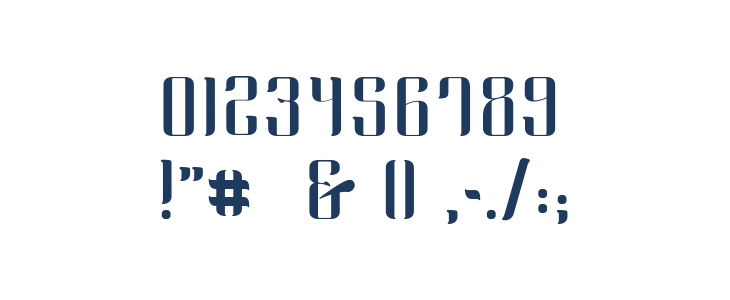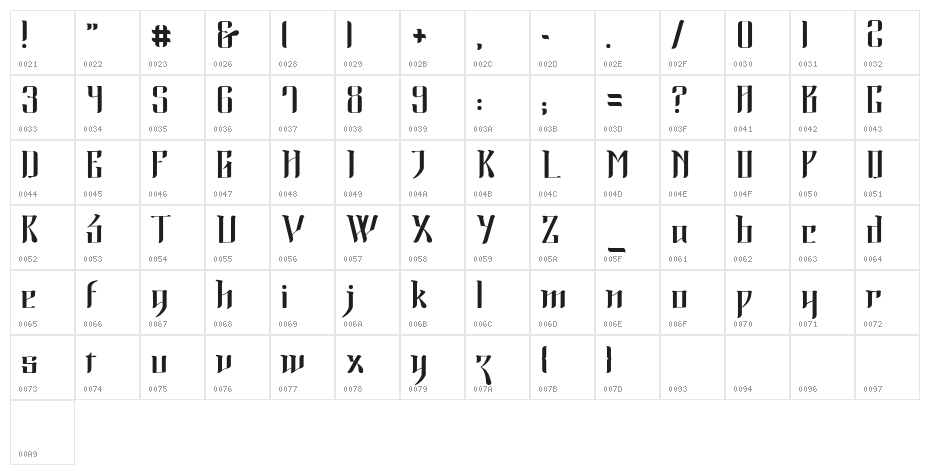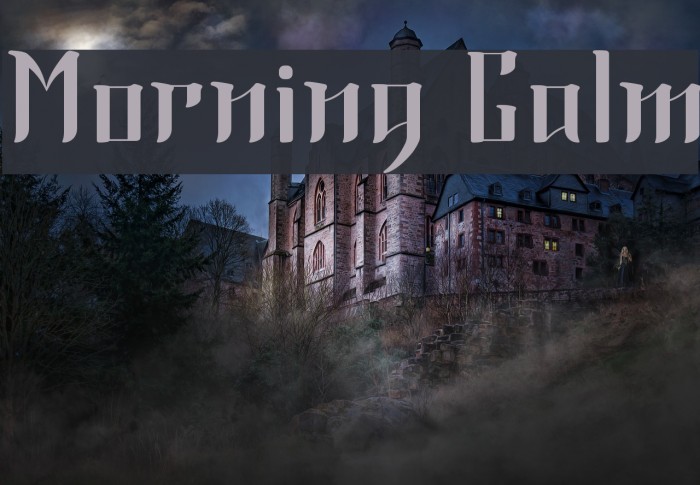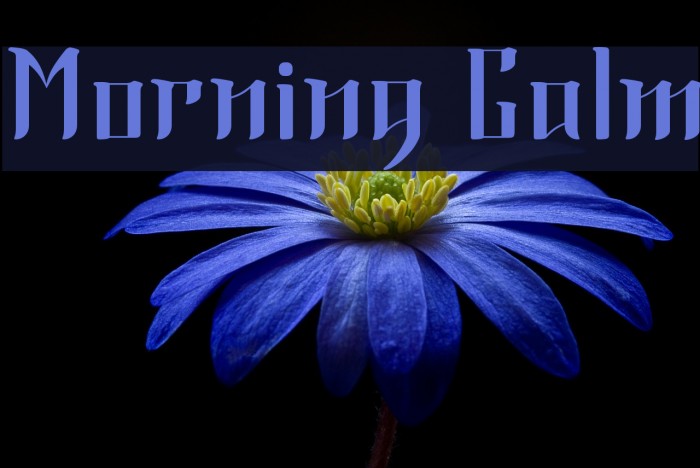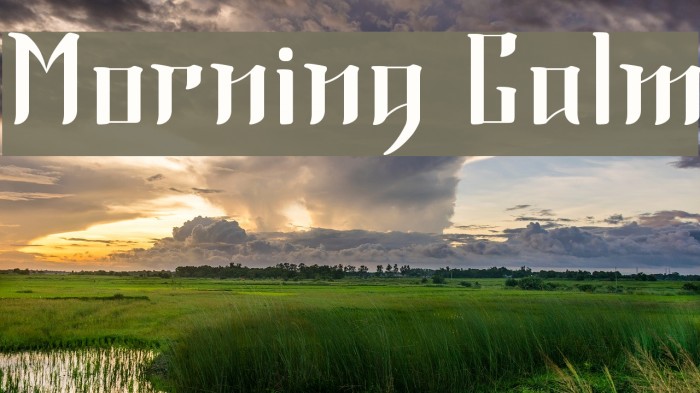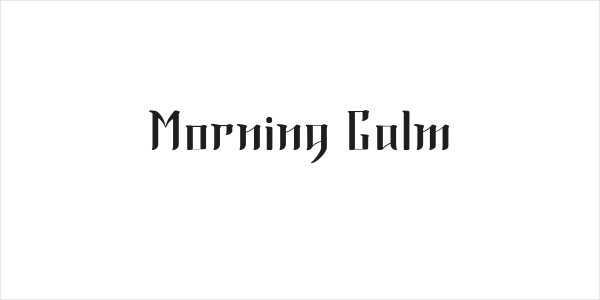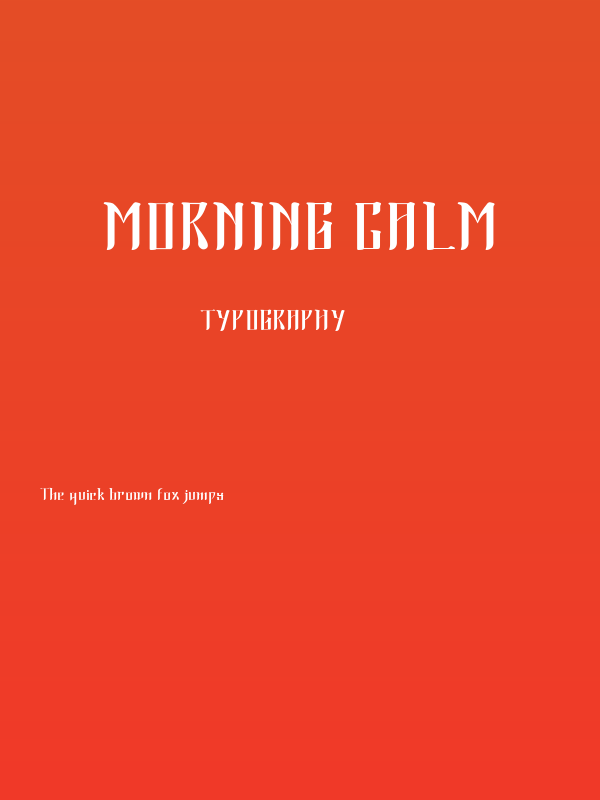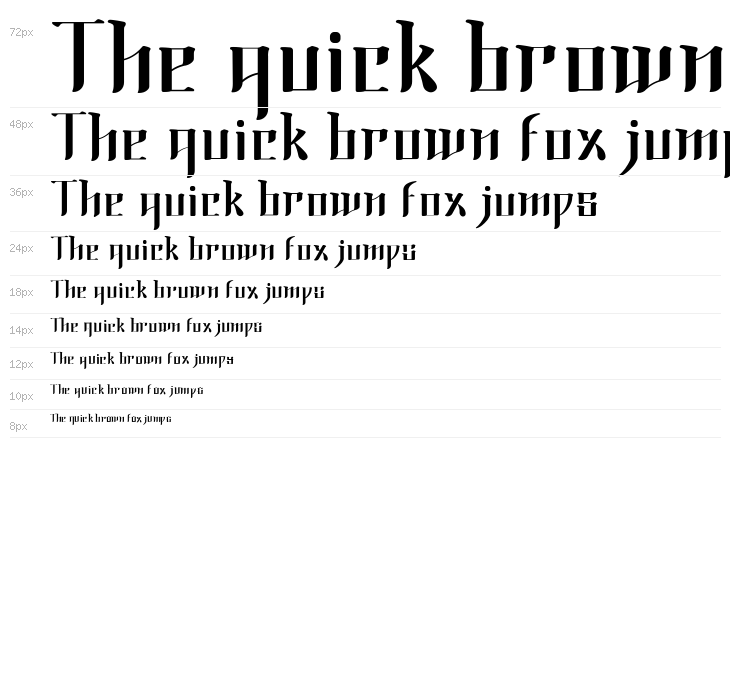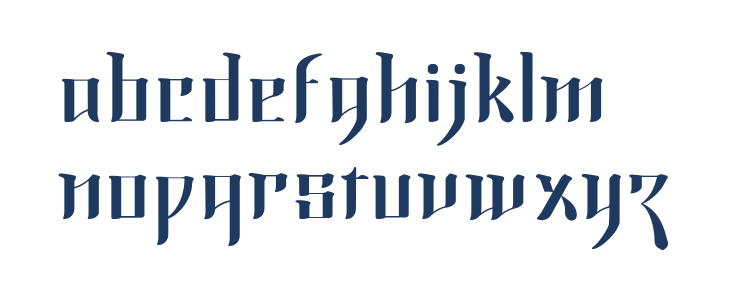
Morning Calm Font
✎ Gothic
| Kategorien | Gothic |
| Gesamtstil | Vintage |
| Vorgeschlagene Projekte | Perfect for medieval-themed designs, book covers, posters, or branding that requires a historical or dramatic touch. |